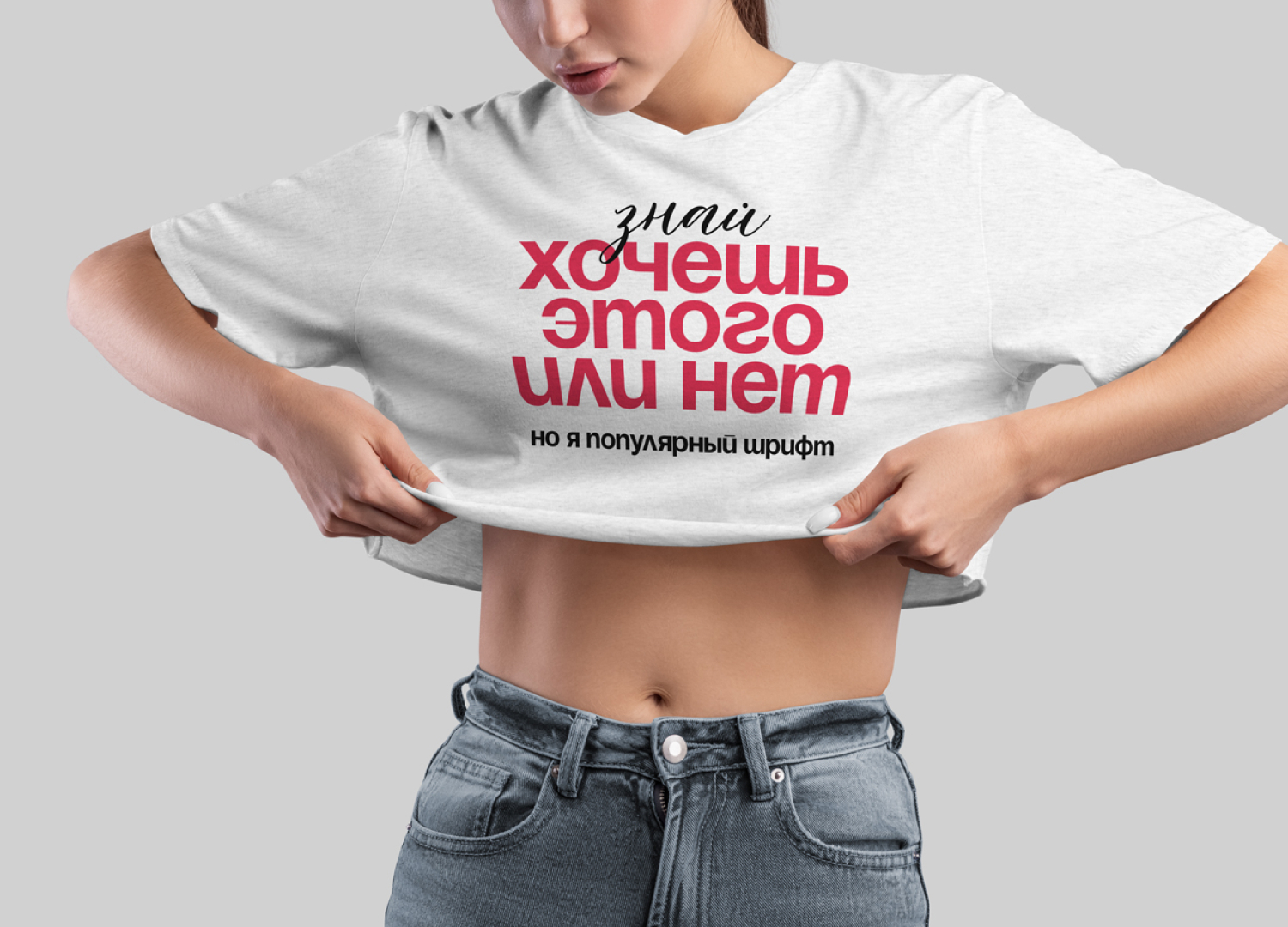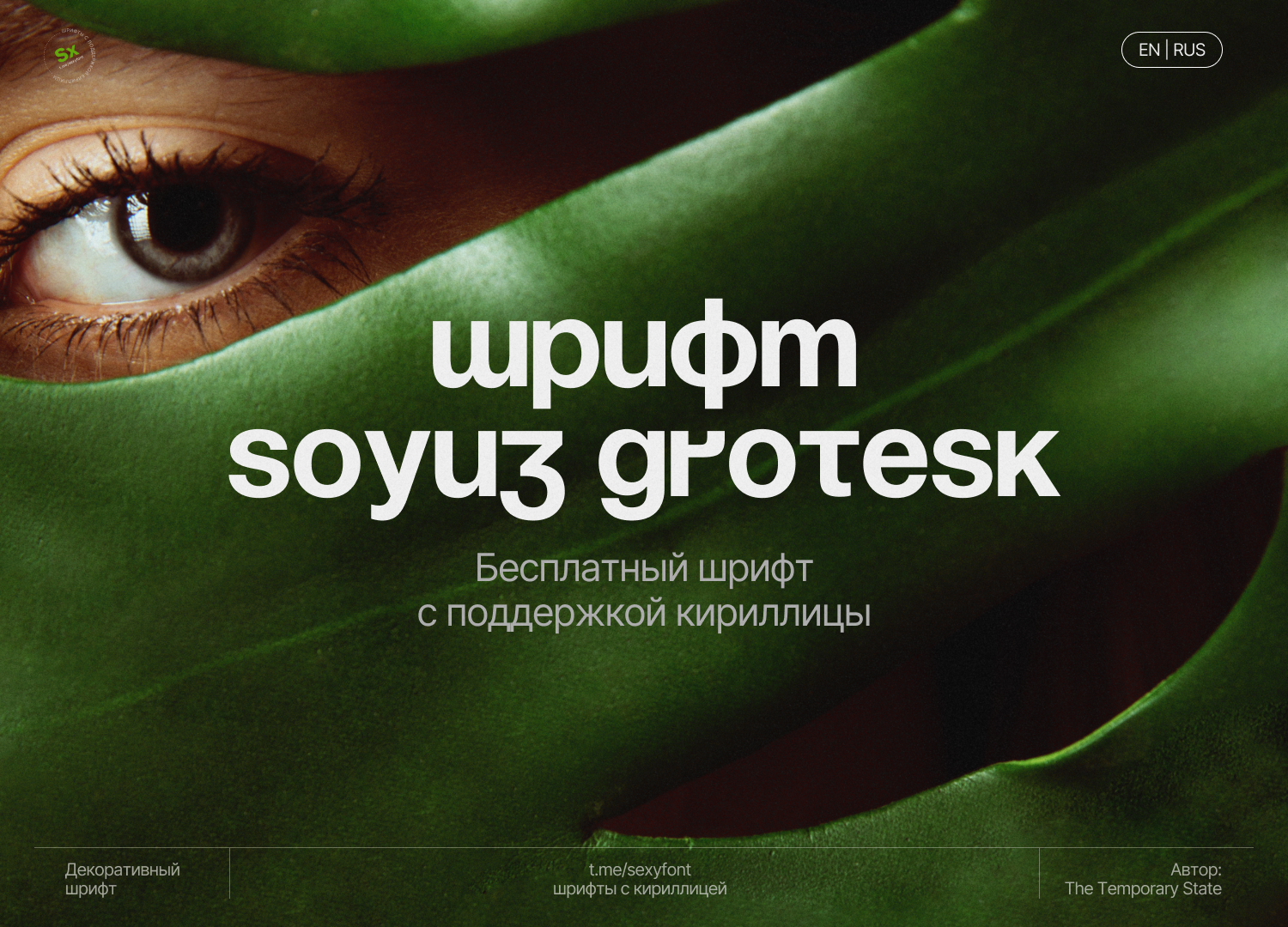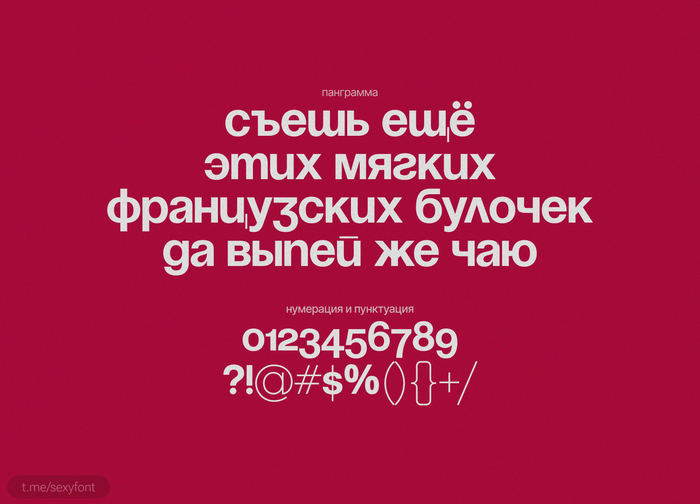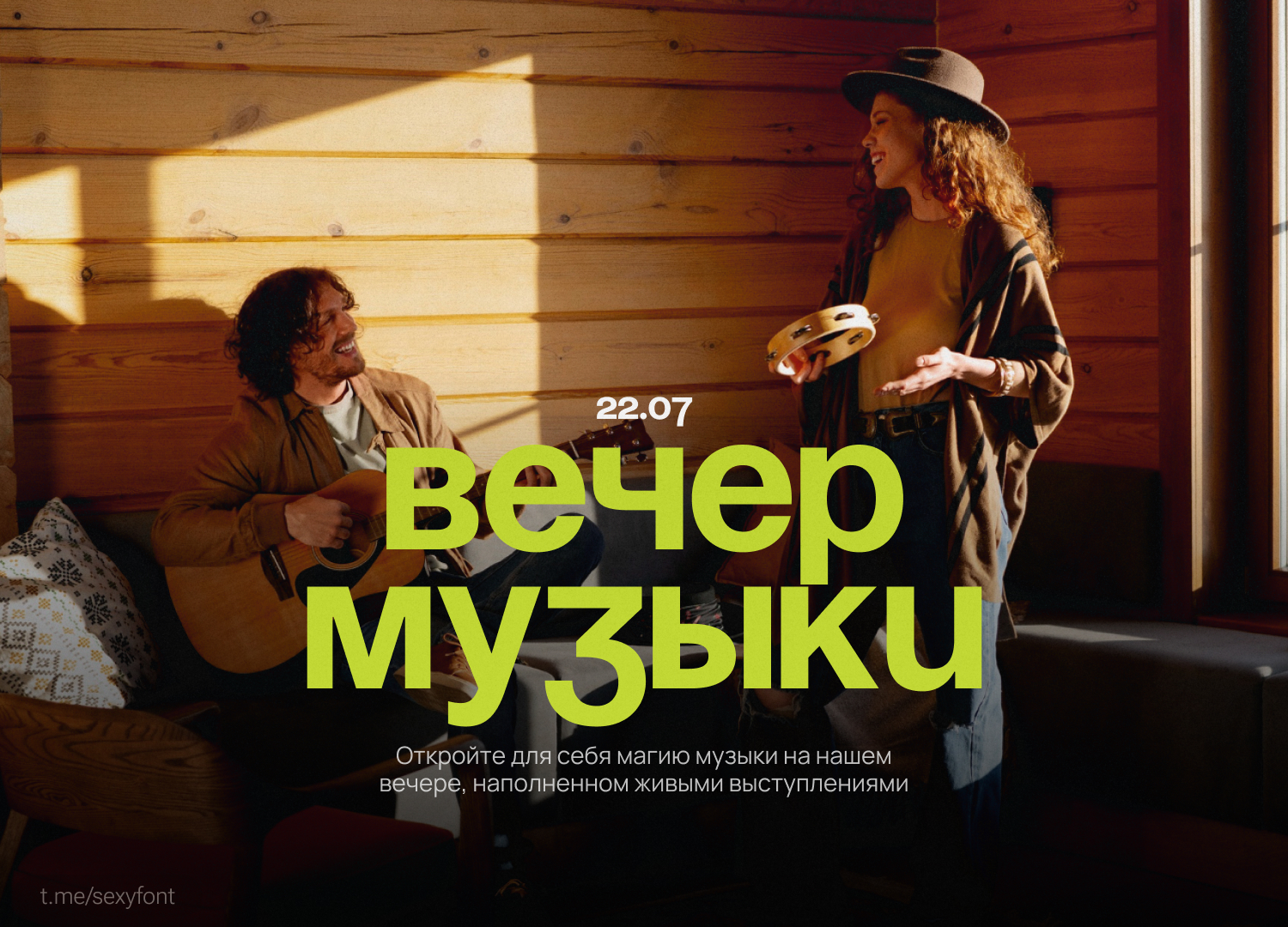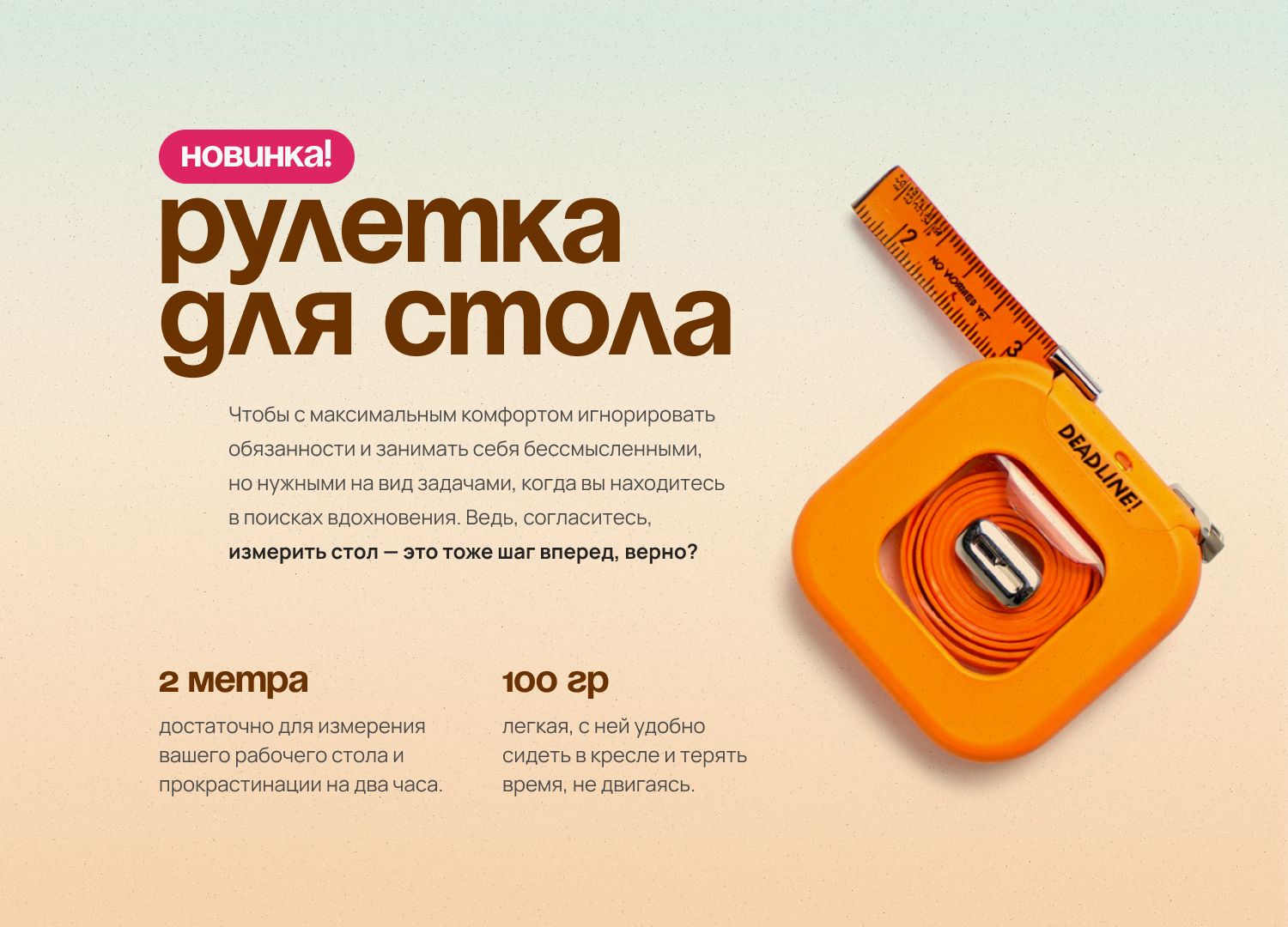
Шрифт Soyuz grotesk
Вы можете его любить или ненавидеть) Но он определенно войдет в историю. Последние пару-тройку лет он везде. Но меня все равно часто спрашивают: «А что это за шрифт?»
Шрифт разработан студентами Московского института печати в 1963 году, Юрием Курбатовым и Максимом Жуковым. Поскольку Helvetica в кириллическом варианте тогда не существовала, они решили сделать свою домашнюю копию. Автор — The Temporary State. На нашем канале он появился впервые уже в конце 2022.